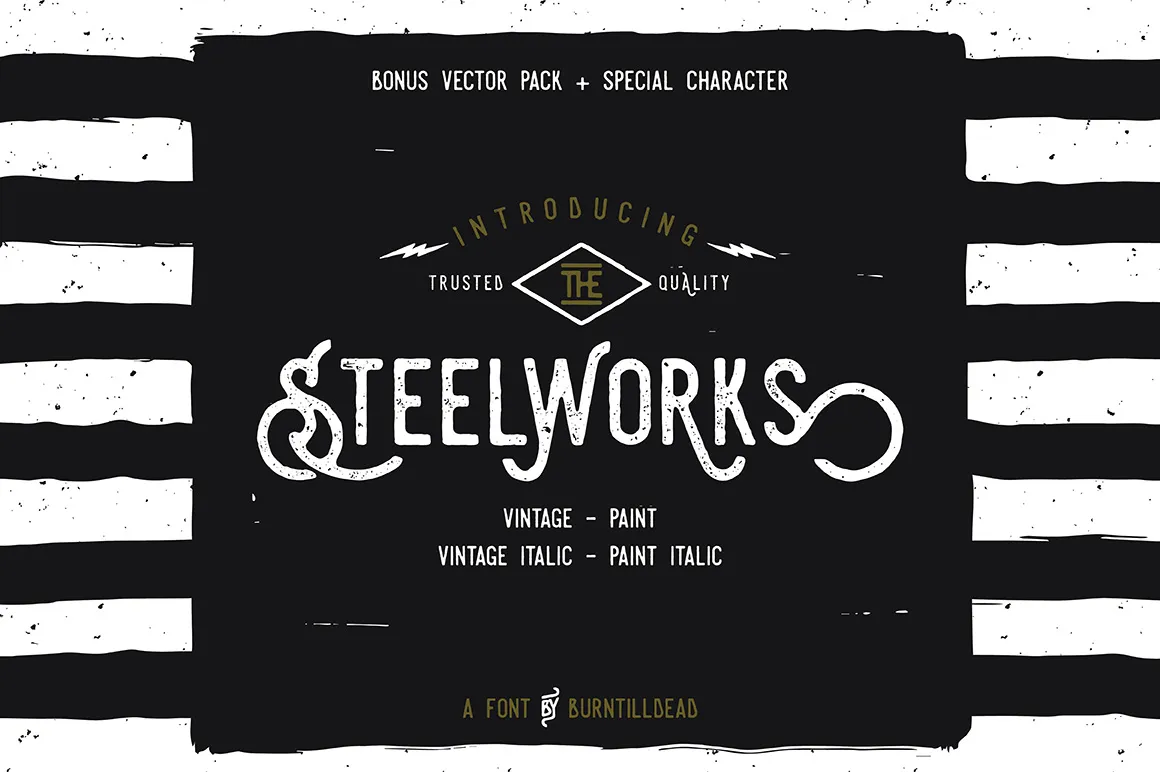
A Fonte ‘Steelworks’ é uma elegante escolha para qualquer projeto que valoriza sofisticação e durabilidade. Desenvolvida pelo designer Hamilton, ela combina formas geométricas modernas com linhas sólidas e fortes, criando um resultado único e atraente. Seu design único de acabamento quase militar fazê-la adequada para qualquer aplicação que exige uma fonte resistente e versátil. Ideal tanto para gráficos de marca corporativa quanto para aplicações publicitárias, ‘Steelworks’ é perfeitamente adaptável à necessidade de sua peça final. Escolha a Fonte ‘Steelworks’ para dar brilho a seu próximo design. E, quem sabe, você pode até fazer uma doação simples em reconhecimento pelo excelente trabalho da designer Hamilton.